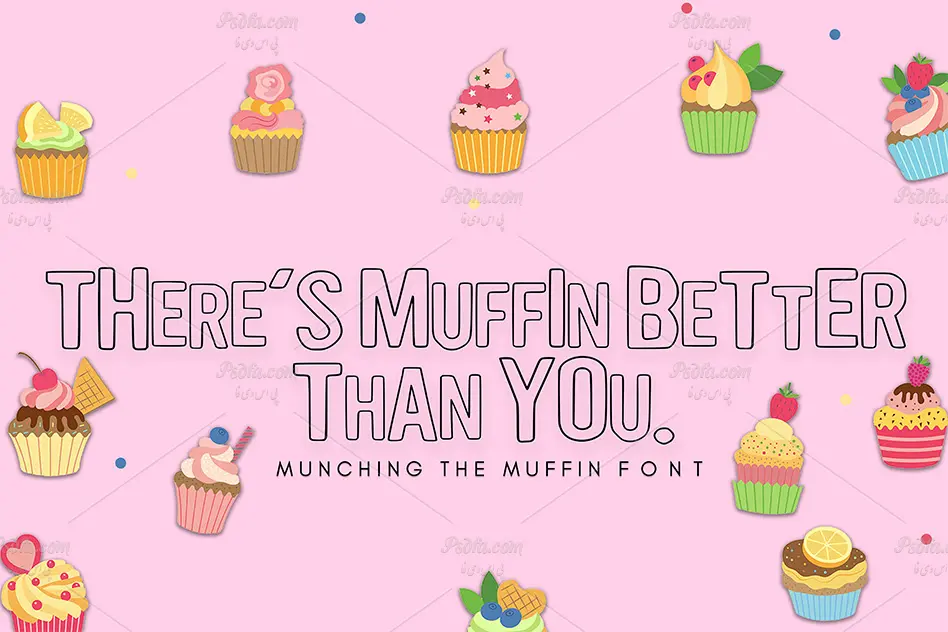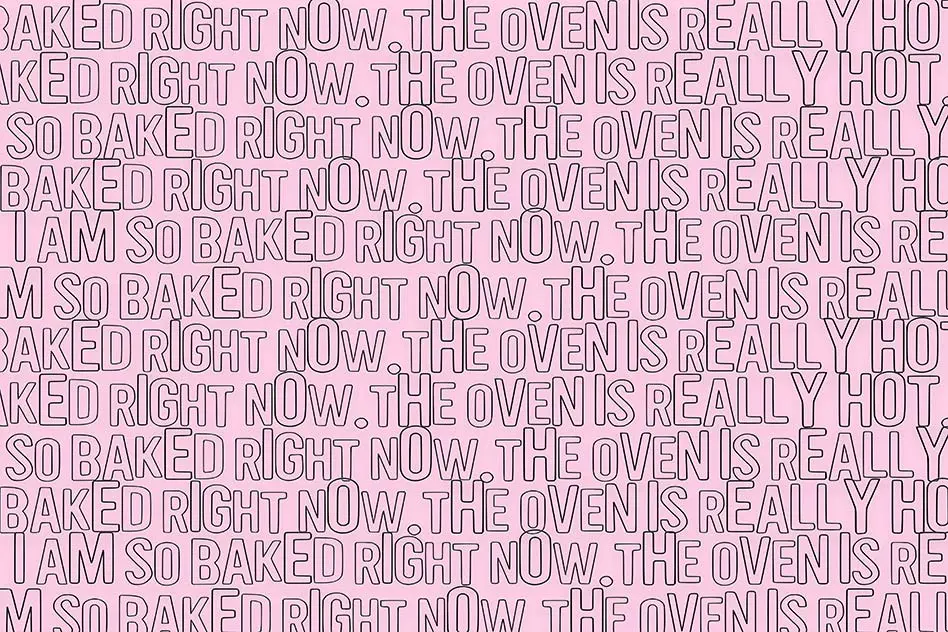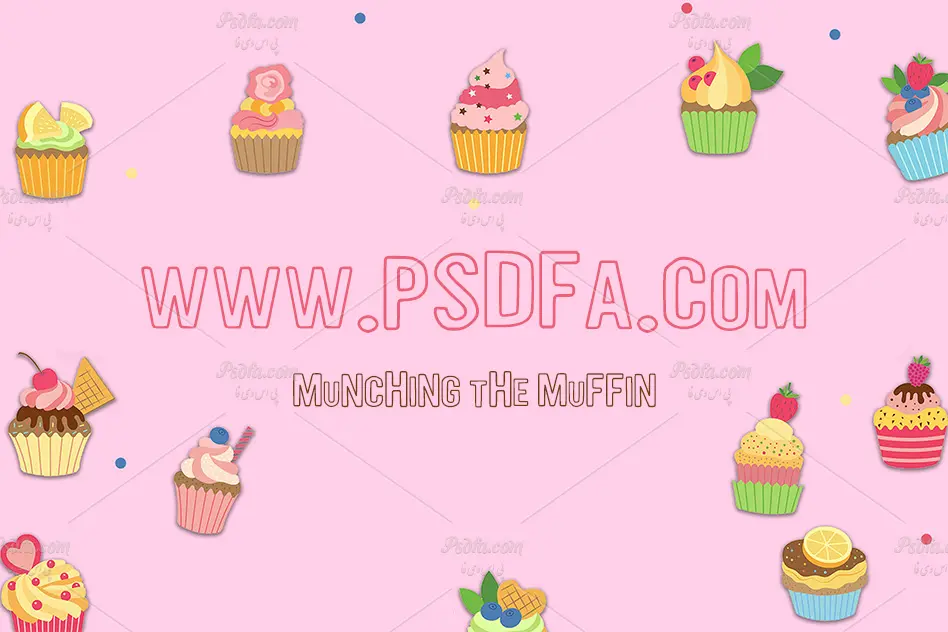
در این مطلب شاهد فونت انگلیسی توخالی Munching the Muffin مناسب جهت استفاده در طراحی و گرافیک می باشید. این فونت زیبا در قالب 2 فایل ttf , otf بر روی سایت قرار گرفته است که با نصب یکی از این دو فایل در پوشه فونت های سیستم قادر به استفاده از آن در تمام نرم افزار های گرافیکی و ویرایشگر متن از جمله نرم افزار فتوشاپ ، افترافکت ، ایلاستریتور ، مجموعه نرم افزار آفیس (ورد ، پاورپوینت) و … خواهید بود. فونت Munching the Muffin در وزن معمولی (Regular) و به صورت توخالی (Outline) طراحی شده است که می توان از آن جهت تایپ عناوین و تیتر طرح های گرافیکی خود استفاده کنید.
- نام فونت : Munching the Muffin
- وزن : معمولی (Regular)